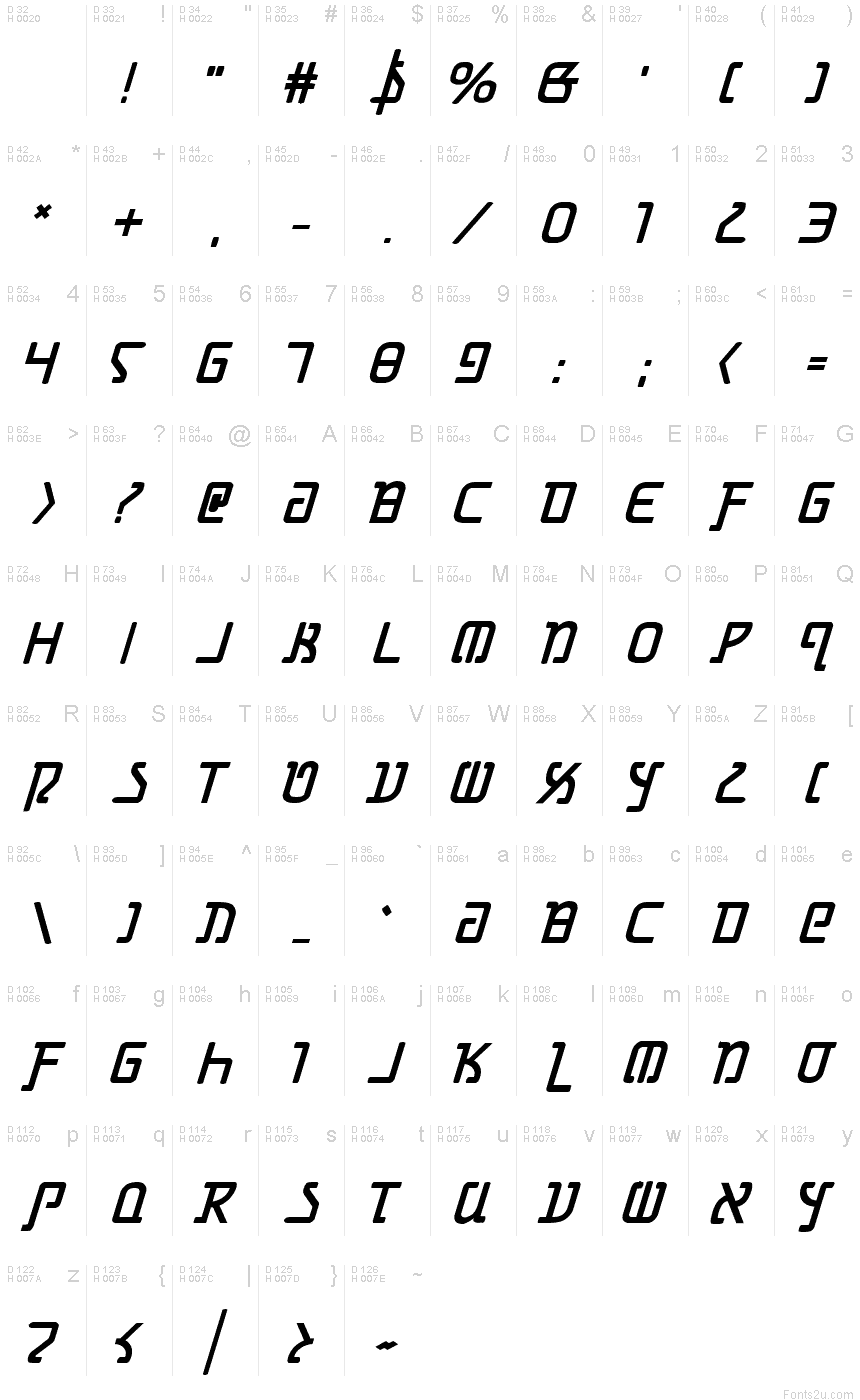
Grimlord Bold Italic autorstwa Iconian Fonts to darmowy, kanciasty, pochylony krój typu display o dynamicznym, ostrym charakterze napisów z automatów do gier i sportów motorowych. Jego silne nachylenie, ścięte rogi i ostro zwężające się łączenia tworzą zwarte sylwetki, podczas gdy zaokrąglone wewnętrzne cięcia sprawiają, że kreski nie wyglądają czysto mechanicznie.
Zestawiony z fotografią wyścigową lub ilustracją science-fiction, krój ten potrafi wzmocnić ruch już obecny na plakatach, grafikach w grach i oprawach muzycznych. Świetnie nadaje się również do identyfikacji wizualnej sprzętu sportowego lub produktów gamingowych, gdzie pochylenie do przodu i niestandardowe kształty mogą ugruntować wyrazistą tożsamość produktu.